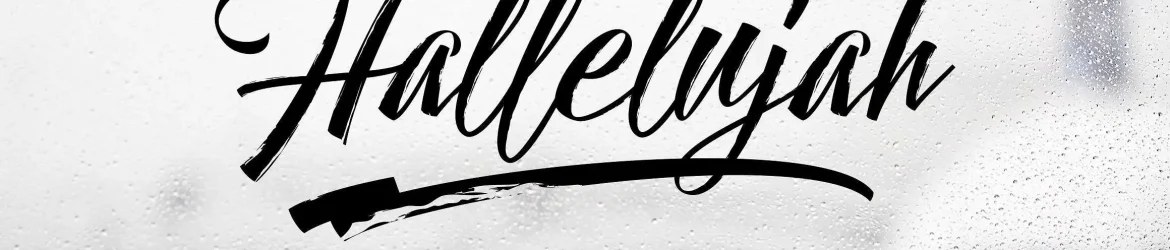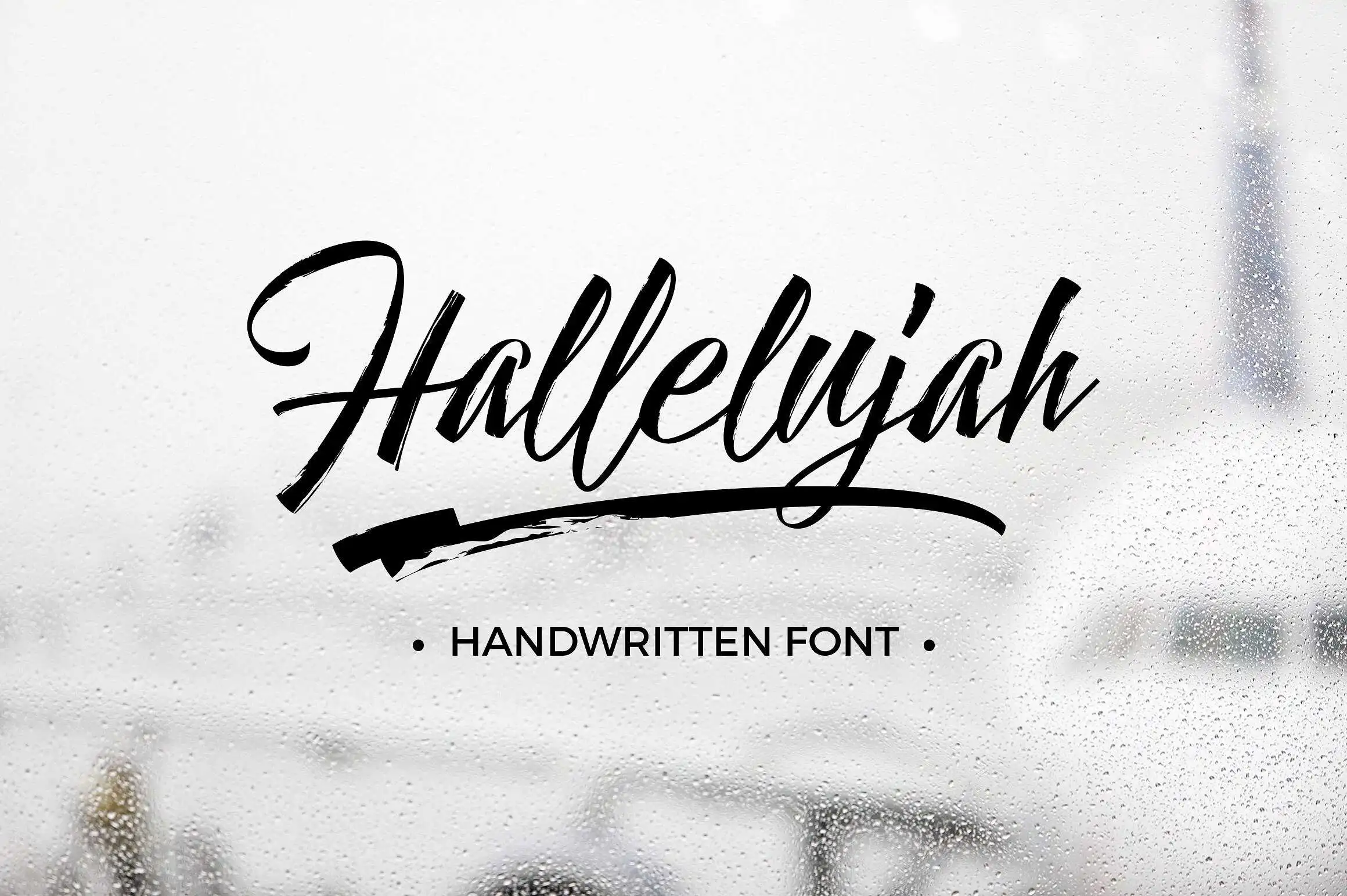
Hallelujah Script Font – Fonte Grátis
Hallelujah Script Font
Introduzimos a Hallelujah Script Font para quem busca uma fonte que transforma qualquer texto em algo belamente elegante. Ideal para estilos de marca, logomarca, cabeçalhos, flyers, roupas, embalagens, cartões de visitas e muito mais, a Hallelujah oferece um toque delicado e sofisticado que fará sua identidade visual brilhar. Com seu design elaborado em desenhos à mão livre por Hamilton, essa fonte script traz uma textura única e vibrante, perfeita para incorporar em qualquer tipo de projeto. Seja você um designer gráfico ou alguém criando material personalizado, a Hallelujah é certamente a escolha perfeita para dar um toque especial à sua arte impressa. Não hesite em experimentá-la; ela se revelará uma fonte indispensável para seus projetos visuais.